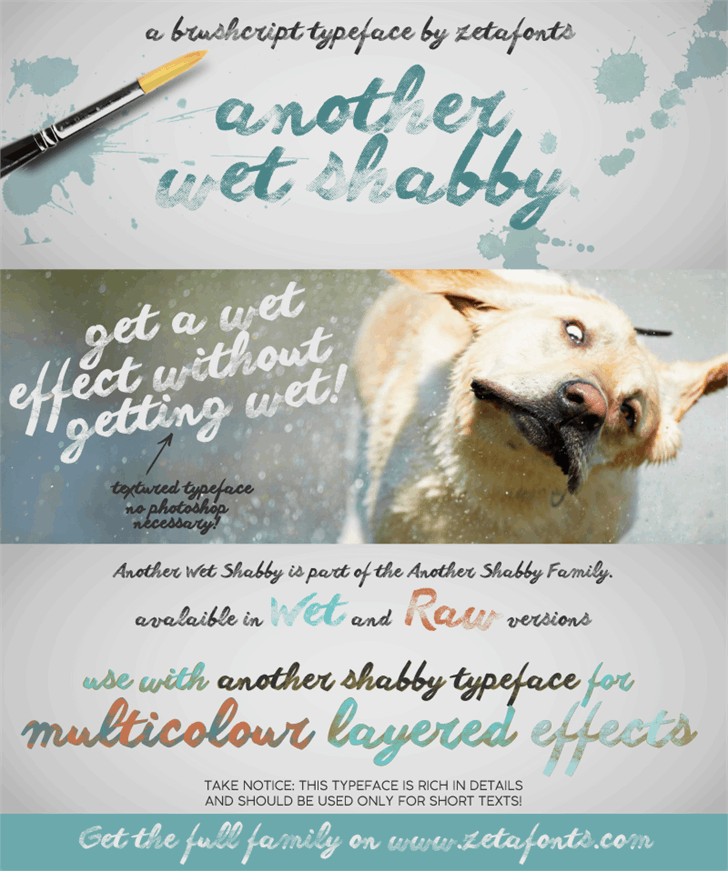
A Fonte ‘Another Shabby’ oferece uma experiência visual única para designers, com sua família de tipografia script criada pelo Francesco Canovaro para a Zetafonts. Sua forma é definida por pinceladas rúnicas e largas que imitam o ar despretensioso da escrita manual casual. A fonte ‘Another Shabby’ inclui suporte para mais de 40 idiomas que usam o alfabeto latino, com uma gama completa de acentos e diacríticos. Seu design engloba quatro pesos familiares, permitindo que os designers criem texturas em imagem multilayered e texturizadas sem precisar recorrer a software de edição de fotos. Além disso, a ‘Another Wet Shabby’ oferece uma textura extremamente sofisticada para criações inspiradoras. Seu uso é indicado para trabalhos que exigem uma qualidade visual rica, mas deve ser cuidadosamente administrado, pois pode consumir muito processamento e causar problemas temporários de desempenho na máquina. A ‘Another Shabby’ está disponível em parágrafos curtos sem danificar o sistema. Seja você designer ou criador de conteúdo, é uma ótima escolha para dar vida aos textos em seus trabalhos, especialmente aqueles que buscam um ar despojado e natural.